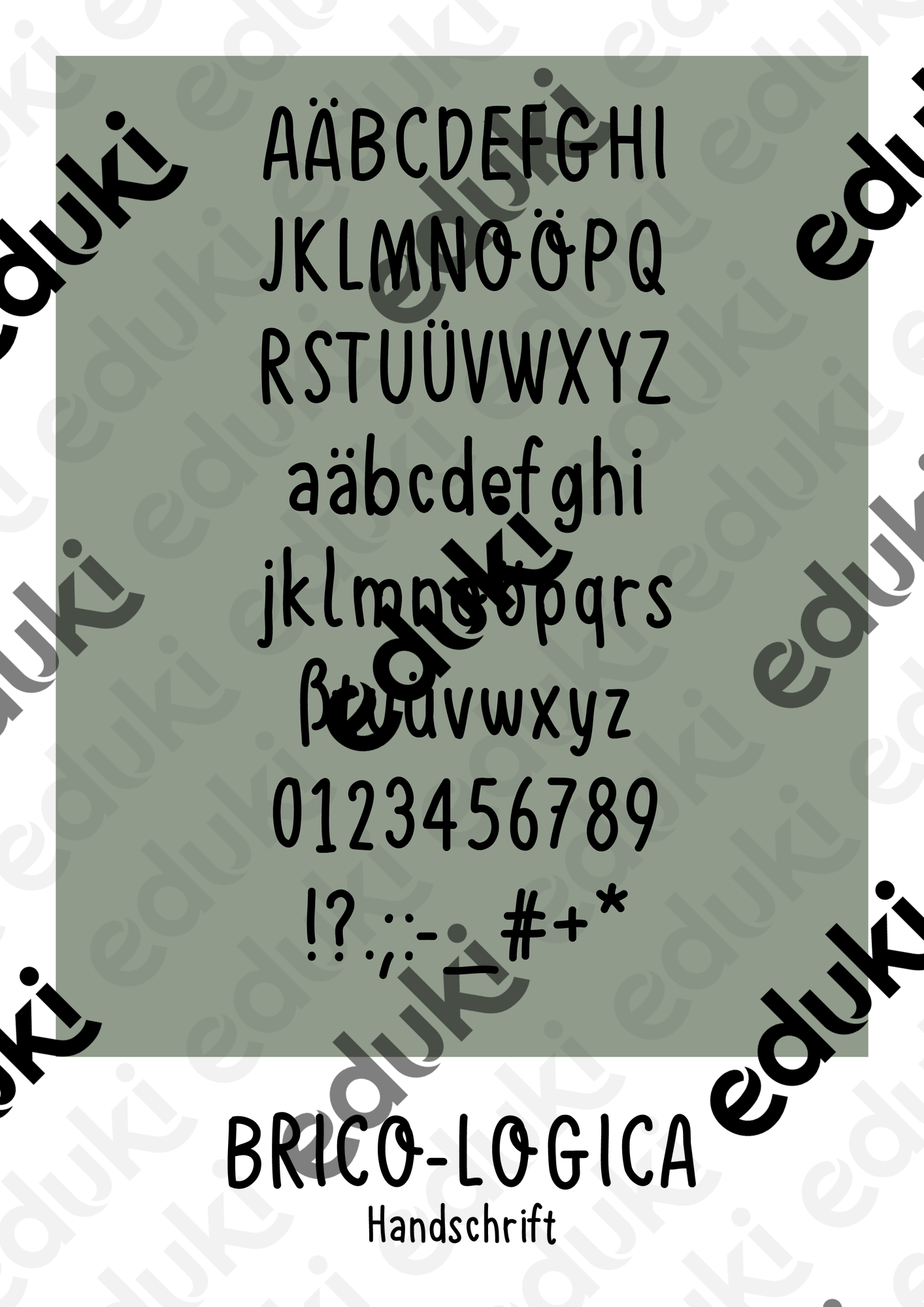
selbst erstellte Schriftarten - Schriftart für dein Arbeitsmaterial - Brico-Logica - Bricoliene - Deckblatt
Selbst erstellte, enge Handschrift, die sich wunderbar zur Erstellung von Arbeitsblättern oder anderem Unterrichtsmaterial eignet. Da die Schriftart sehr eng läuft, eignet sie sich super um Texte platzsparend und hübsch in Szene zu setzen.
Schriftart für dein Arbeitsmaterial - Brico-Logica